- Появились полноценные строчные знаки (капительные формы из предыдущей версии теперь можно найти в капительном наборе);
- Появились цифры (от 0 до 9) и валюты для минускульных и минускульных табулярных цифр;
- Общее количество знаков в каждом начертании выросло с 1341 до 1445;
- Появились новые стилистические сеты: SS04 — Alternative Straight Forms, SS05 — Alternative Rounded Forms, SS06 — Alternative r, SS07 — Alternative l, SS17 — Serbian localization;
- Появились новые OpenType фичи — их количество выросло с 31 до 38.
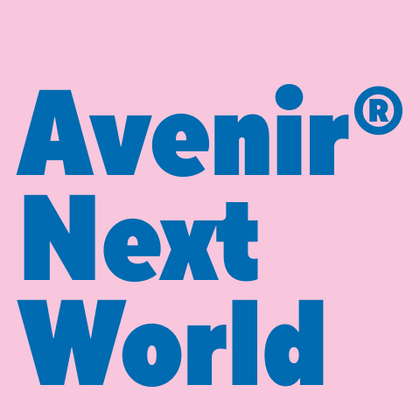
TT Firs Neue — сбалансированный гротеск со скандинавскими мотивами. Это выразительный и привлекательный, при этом лаконичный и универсальный в использовании шрифт. Переиздан дважды, чтобы быть безупречным.
TT Rounds Neue — мягкий и дружелюбный шрифт, который умеет быть разным. В тонких начертаниях он выглядит минималистично и нейтрально. В жирных же — «надувается» и округляется, приобретая инфантильные черты.
TT Fors — тот самый шрифт «для всего». Это стильный, лаконичный и функциональный геометрический гротеск с выверенными формами. Его можно использовать и в интерфейсах, и для создания акцентов.
TT Ramillas — стильная и современная антиква, которая украсит любой проект. Уникальные декоративные начертания и буквицы с цветочным орнаментом помогут создать неповторимый дизайн. Шрифт уже используется на 3000+ сайтах во всем мире, а также отмечен наградой Modern Cyrillic.
TT Octosquares — октагональный гротеск с футуристическим характером. Этот шрифт отличается геометричностью и своеобразной «мозаичностью»: он как бы собран из отдельных фрагментов, что проявляется и в мельчайших деталях.
TT Runs — это выразительный шрифт, который идеально впишется в проекты со спортивной тематикой. При этом гарнитура отлично подойдет и для других современных проектов: после обновления сфера ее применения значительно расширилась.